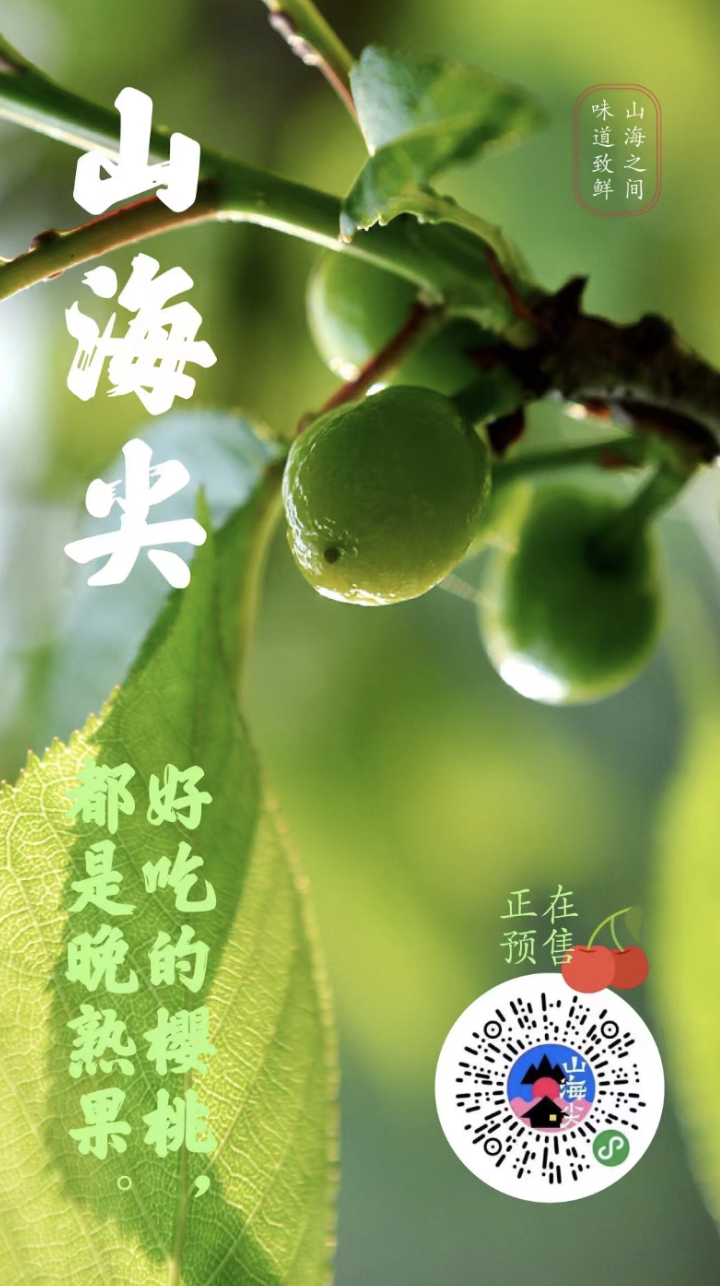
方正石门铭楷书
楷书
关于石门铭:
《石门铭》又称《泰山羊祉开复石门铭》。北魏永平二年楷书摩崖石刻,由王远撰文并书丹。该刻石笔阵森严、气势雄峻、书风自然开张、意趣天成,表现出大朴不雕的阳刚之美,是北魏摩崖石刻的代表。
字体特征:
字体以《石门铭》为临创开发依据。字形偏扁而有长画飞逸,使字的结体有张有弛、舒展宽绰;结体朴拙,结构诡异;字体线条苍茫圆浑,而偶有笔画似童稚信笔所为,稚拙中寓朴厚,耐人寻味。
应用场景:
电商、品牌、海报、杂志、书籍、包装、广告、招牌、新媒体、影视、动漫等